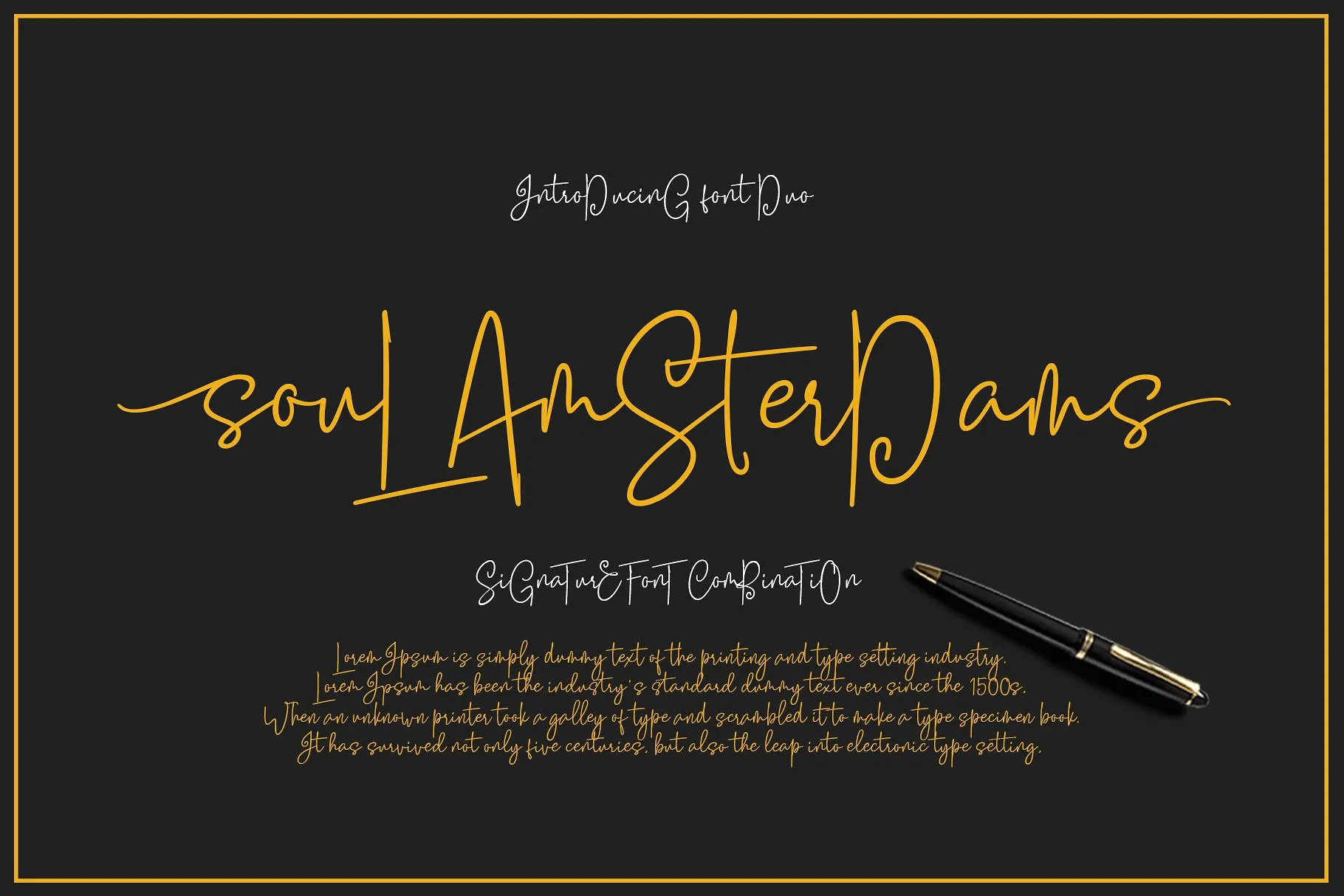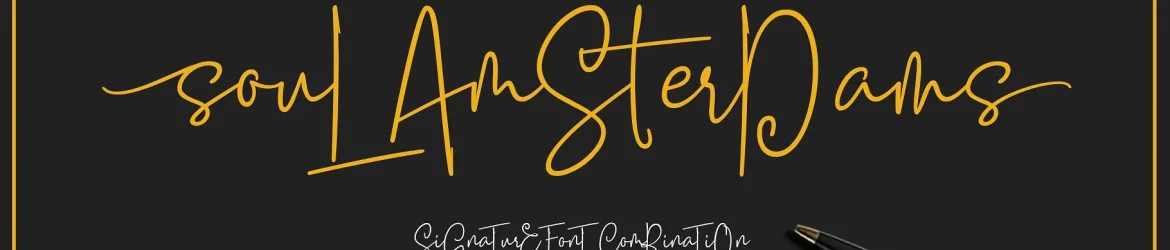
Descubra uma nova adição à sua biblioteca de fonts modernas com a Sool Amsterdams Script Font. Esta nova fonte script é perfeita para criar letras impactantes e únicas, combinando elementos clássicos do calligrafismo com estilos contemporâneos. Introduzimos “Soul Amsterdams”, uma fonte de estilo moderno que incorpora nuances de linha cromada num design elegante e moderno. Já conhecido é o “Soul Amsterdams Duo” – outro belo exemplo desta abordagem original, combinando a estética do calligrafismo tradicional com linhas contemporâneas. O resultado? Uma fonte que oferece uma sensação de simplicidade e elegância, sem perder aquela pegada moderna e criativa. A Sool Amsterdams é uma opção perfeita para designers em busca de um novo elemento único na sua paleta de recursos gráficos. Com alternativas incluídas e ligaturas ajustadas para facilitar a criação de textos lindos, a fonte oferece flexibilidade e versatilidade que vai agradar todos os tipos de projetos digitais. Seja você um designer gráfico ou um artista digital criativo, explore a versatilidade da Sool Amsterdams Script Font. É mais do que uma ferramenta; é uma adição notável à sua coleção de recursos gráficos para criar letras verdadeiramente únicas e imprimíveis.